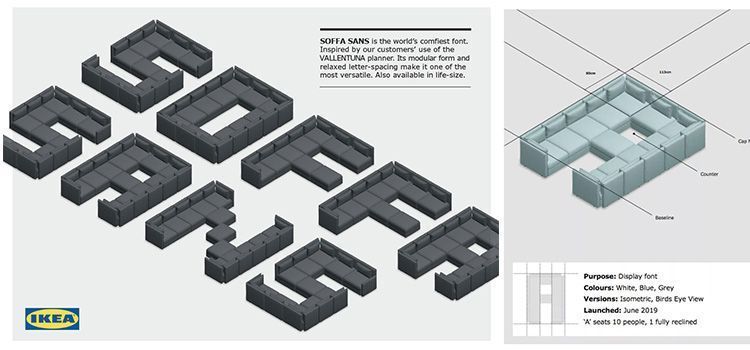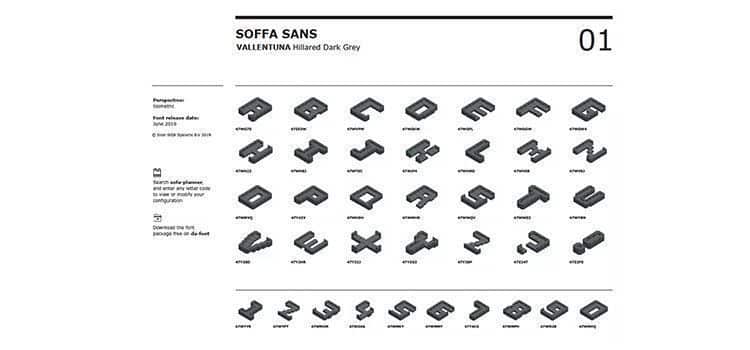
La tipografía de Ikea realizada con sofás: «Soffa Sans»
La tipografía de Ikea realizada con sofás pretende demostrar la nueva herramienta de planificación de sofás.
Ahora desde Ikea London nos sorprenden con la creación de una tipografía hecha con sofás: La «Soffa Sans».
Y es que la nueva tipografía de Ikea se inspira en la nueva herramienta de planificación de sofás de la compañía. Una herramienta tan potente que puede dar forma a todas las letras y números del abecedario. Realizada por Proximity London mediante el software Vallentuna de Ikea podremos dar forma a signos, letras y números.
Según Marcos Tejedor, responsable de ventas de Ikea Reino Unido. “Disfrutamos viendo cómo se divierte la gente con nuestros sofas y cómo crean innovadoras soluciones. Inspirados en su creatividad, lanzamos «Soffa Sans», la tipografía más cómoda del mundo. Su forma modular y el amplio espacio que deja entre los caracteres hace que sea una de las tipografías más versátiles del mercado. Estamos deseosos de ver dónde se usa.”